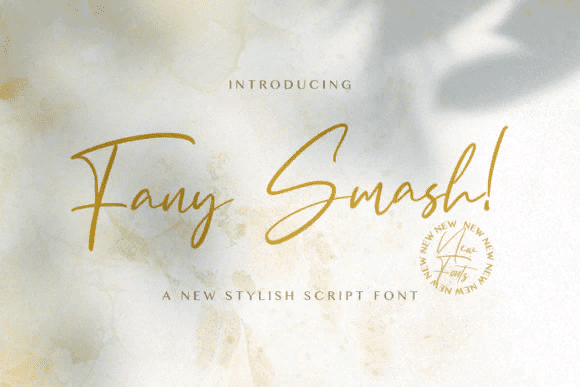
Название: Fany Smash Font
Fany Smash - это элегантный и изящный рукописный шрифт с милыми и нежными мазками.
Этот оригинальный шрифт подойдет для широкого круга рукодельных идей, от бланков и заголовков до канцелярских принадлежностей.
Название: Fany Smash Font
Fany Smash - это элегантный и изящный рукописный шрифт с милыми и нежными мазками.
Этот оригинальный шрифт подойдет для широкого круга рукодельных идей, от бланков и заголовков до канцелярских принадлежностей.